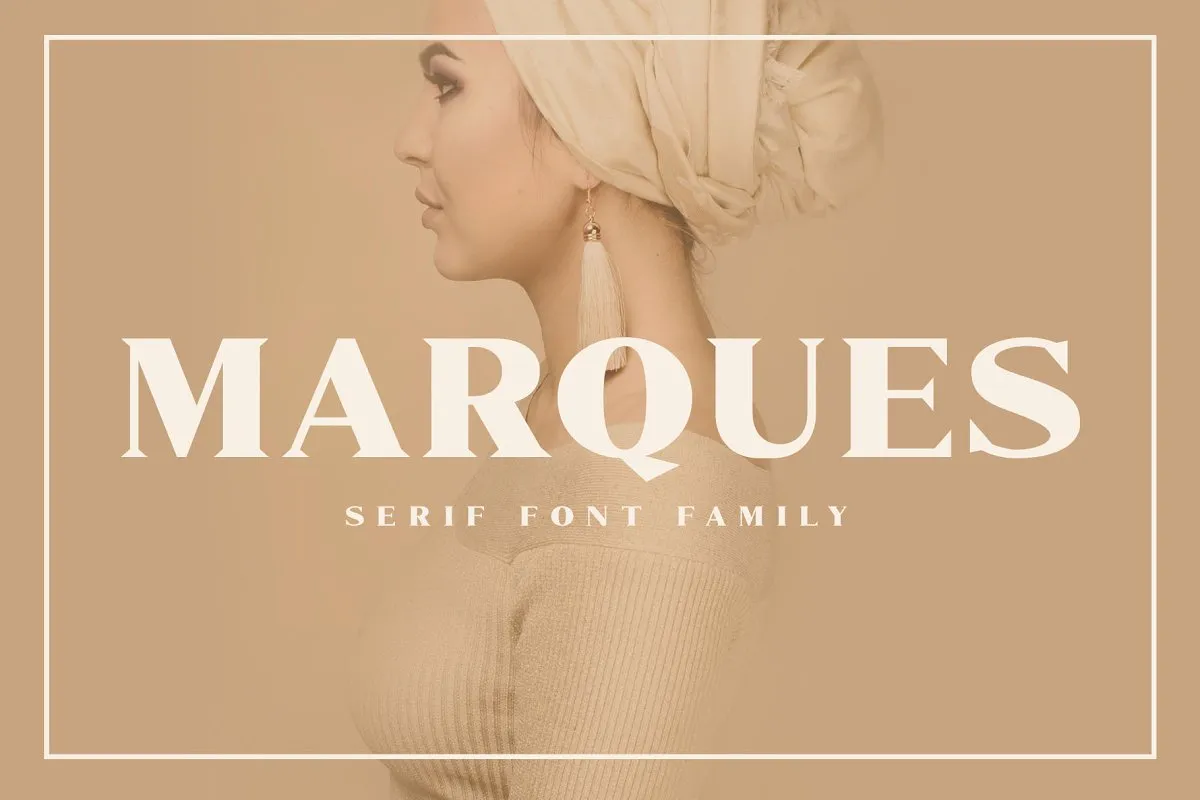
Marques Font Family – Download Grátis
A Marques Font Family é uma nova família de serif feita para designers que buscam uma solução fresca ao procurar fontes para projetos específicos. Se você estiver buscando um tipo moderno, pode encontrar a inspiração perfeita nesta família. A Marques Font Family traz elementos de simplicidade e confiabilidade em seu design, marcados por traços com baixa contraste, formas redondas levemente quadradas e um ar de simplicidade bem-humorada que remete à estética moderna sem serif. Esta família foi criada pelo Craft Supply Co., oferecendo a designer uma fonte ideal para projetos que exigem elegância clássica e simplicidade pura. Ideal tanto para criações comerciais quanto para textos mais formais, a Marques Font Family é uma escolha inteligente para designers buscando um equilíbrio perfeito entre estética e funcionalidade.